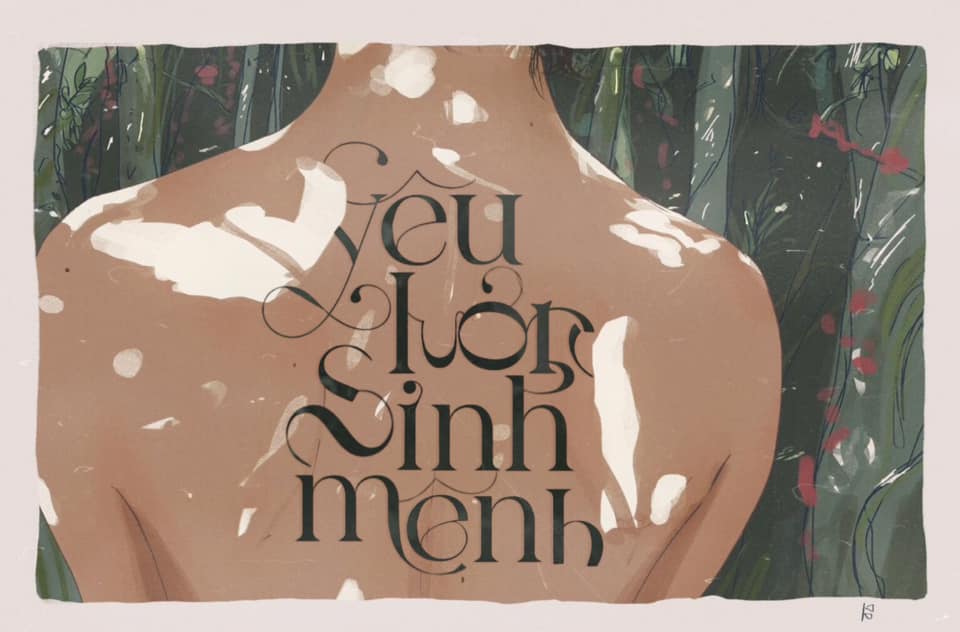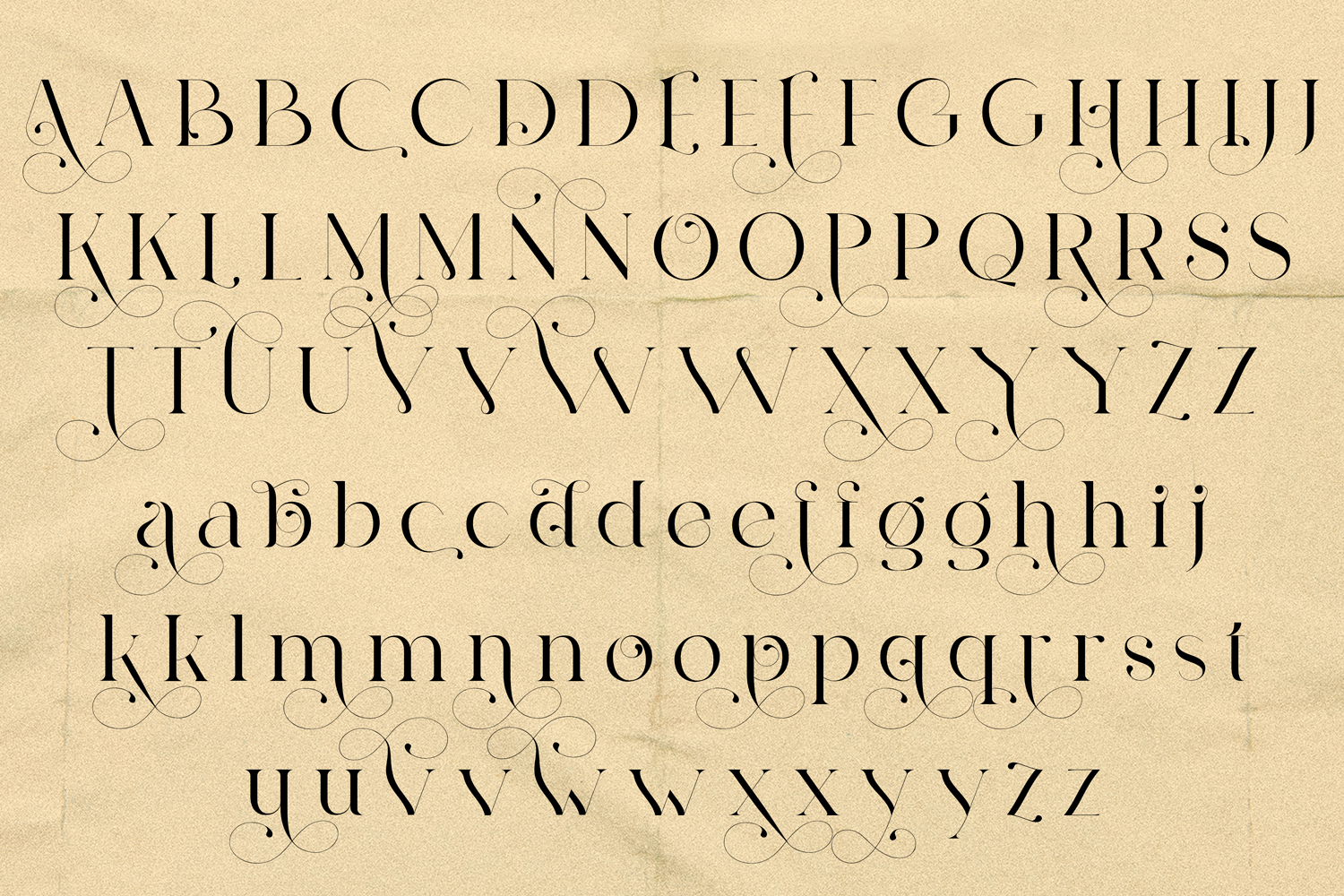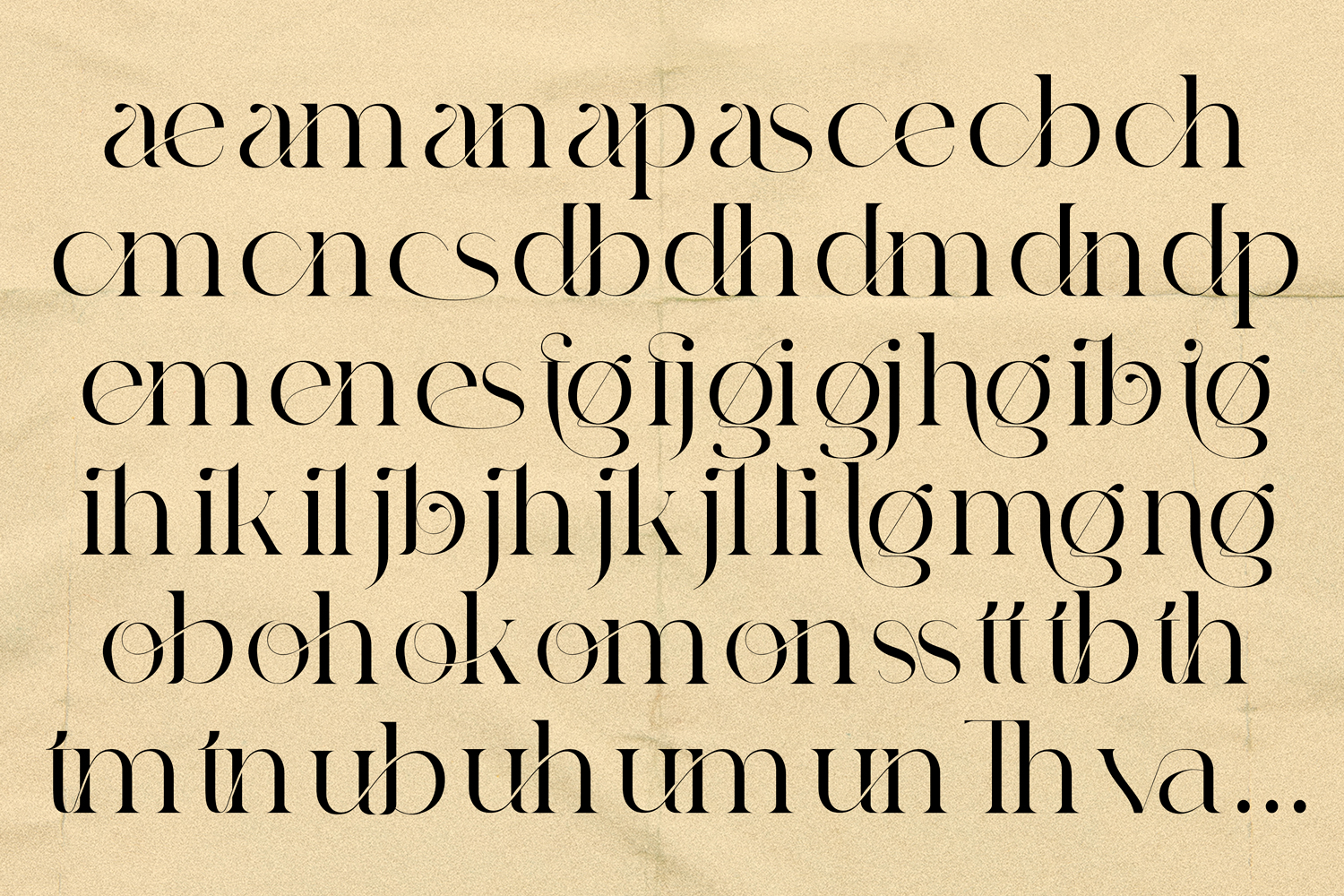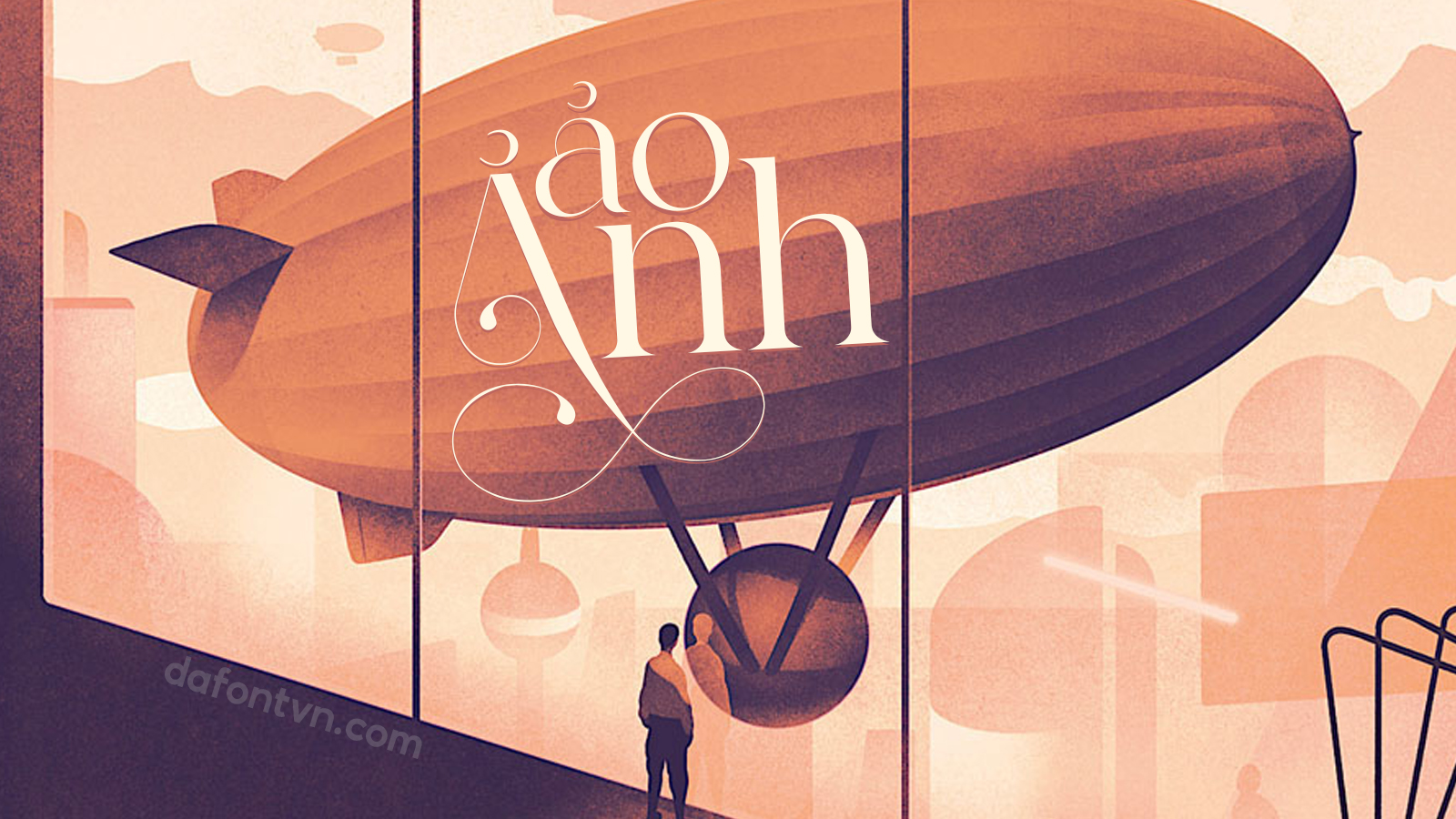
Font Gangitem Việt Hóa một phông chữ serif hiện đại và ấn tượng. Font còn bao gồm các chữ ghép để cung cấp cho bạn tất cả những gì bạn cần để có được những thiết kế phá cách. Phông chữ này vừa hiện đại, vừa hoài cổ và rất phù hợp cho các thiết kế tiêu đề, trích dẫn… hoặc bất kỳ thiết kế nào khác